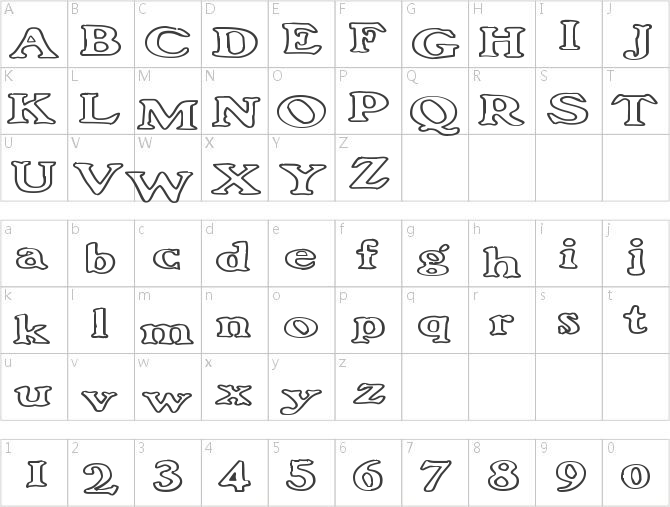
字體名稱: Franken
FrankenFont Large Hollow
FrankenFont Large Hollow介紹
FrankenFont Large Hollow字體字庫是一款讓人賞心悅目、百看不厭的英文字體,適合各類廣告和產品包裝設計應用,字體大小0.13MB,格式為ttf字體,上傳用戶是13226568769,作者/版權方為未知